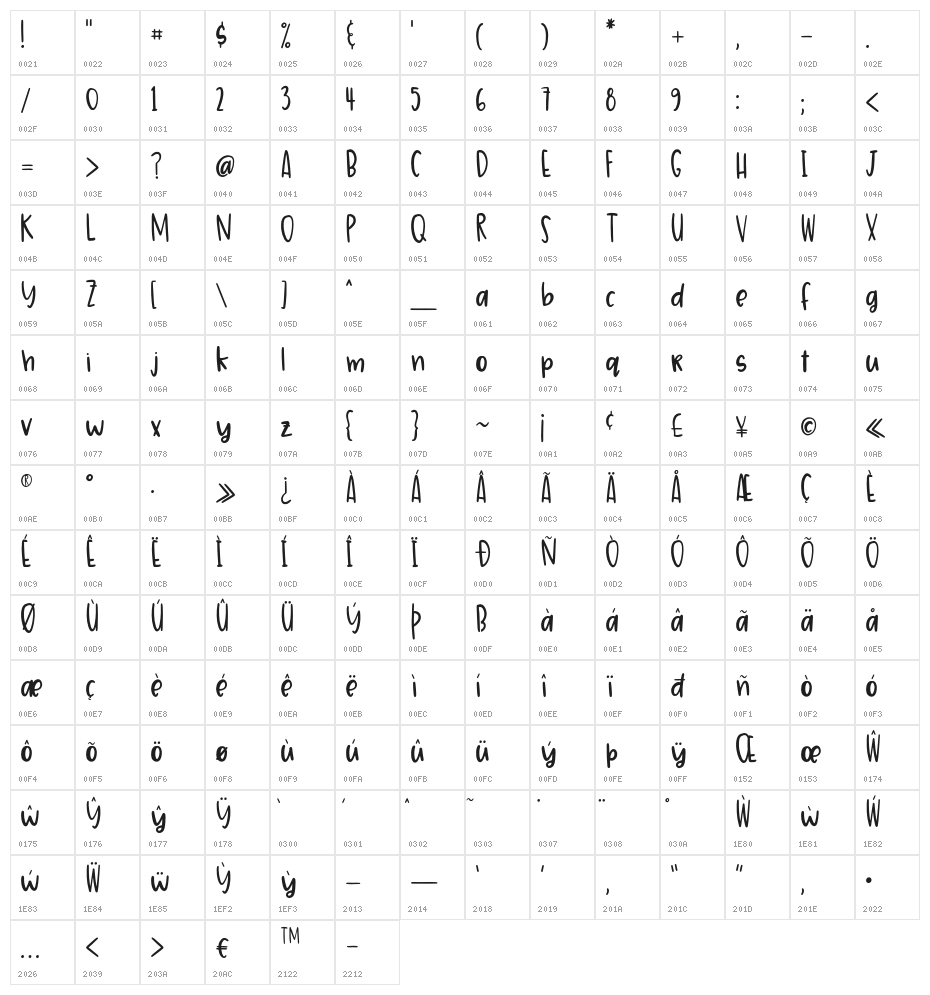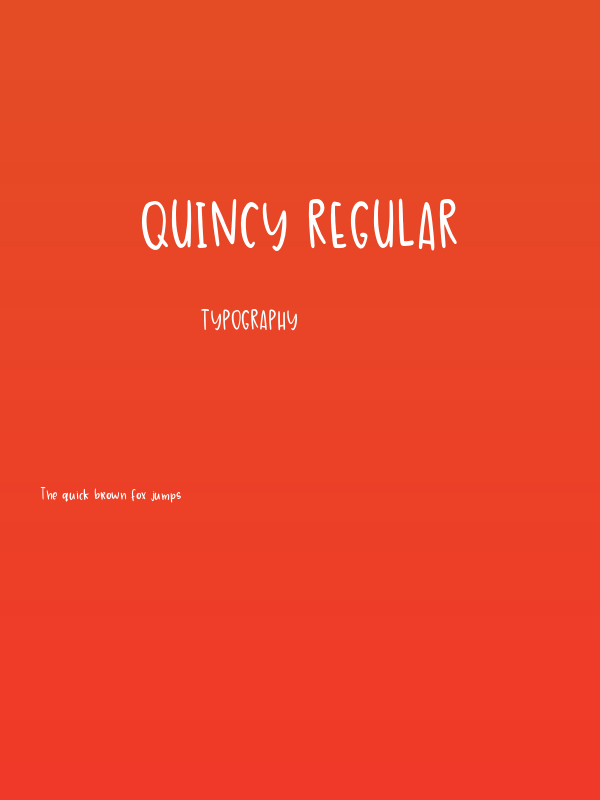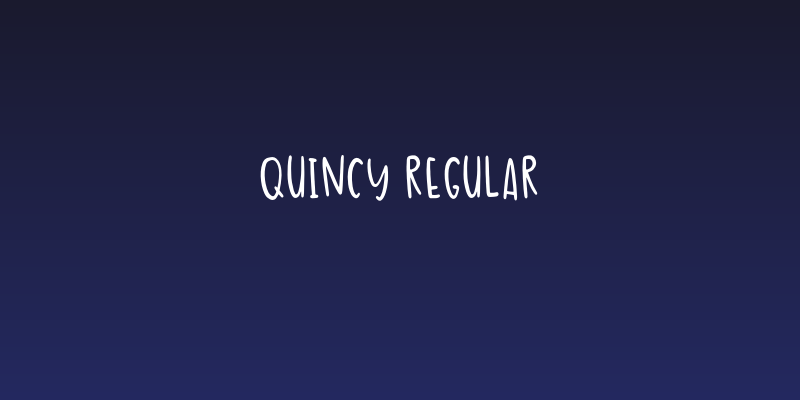
Quincy Regular Font
| Stile generale | Casual and playful |
| Caso d'uso | Headlines, Informal text, Branding |
| Progetti proposti | Ideal for greeting cards, children's books, personal blogs, and informal branding. |